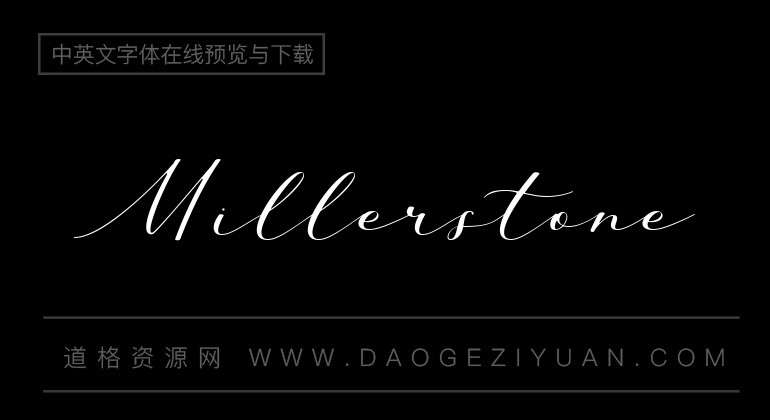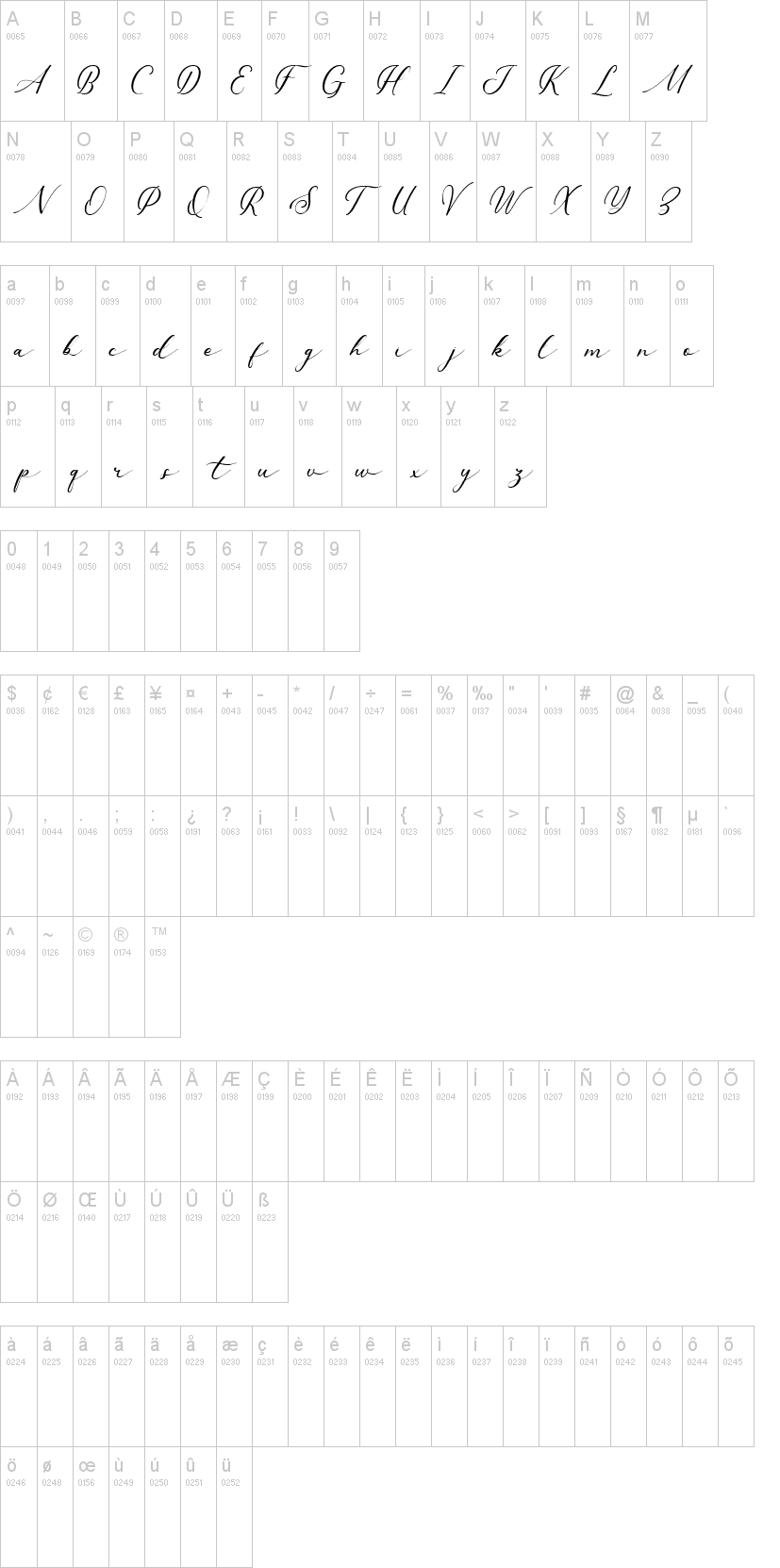
Millerstone
Millerstone 是一种简洁、现代、多功能的英文字体,它有着简约而优雅的外观,可以用于各种不同的设计项目。Millerstone 字体具有清晰的细节,可以提供清晰的文字效果,更好地传达您的设计理念。它的特点是它的字符间距较大,可以更容易地识别文字,使文字更易于阅读。Millerstone 字体适用于各种不同的设计,包括印刷、网页设计、品牌设计、广告设计等等。
Millerstone是一款非常不错的手写艺术字体,具有很好的视觉感,适合于文化类的宣传设计、商业类品牌的广告和产品包装设计以及个性化文字排版等较多场景。
Millerstone字符映射图